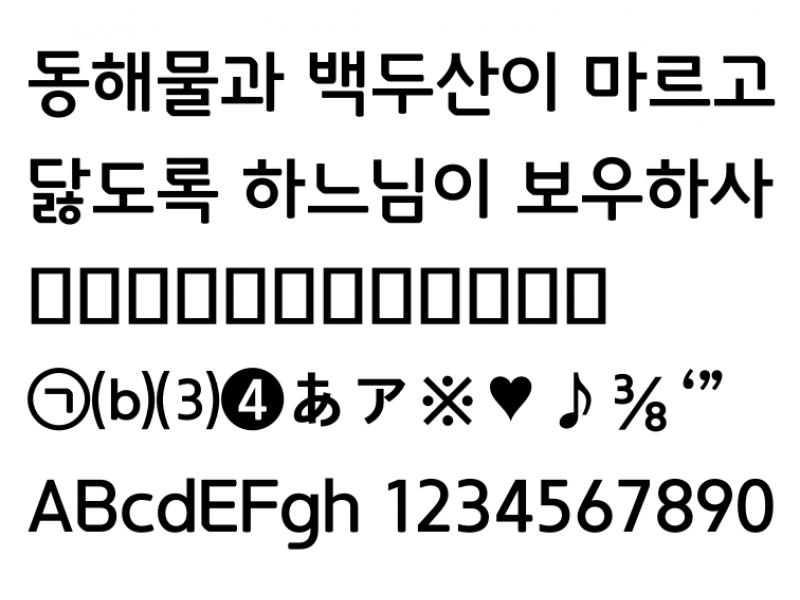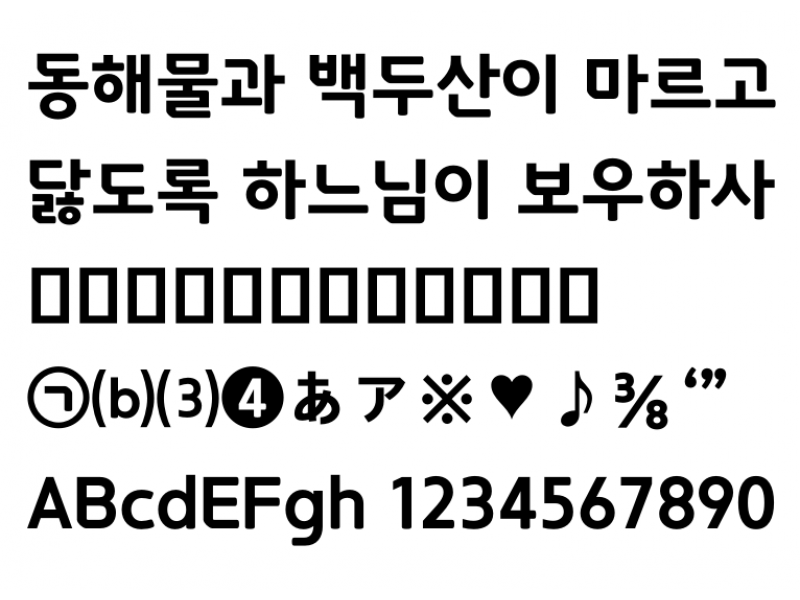
고도체는 엔에이치엔고도와 윤디자인연구소가 협력하여 만든 다이아몬드 형태의 심플하고 모던한 디자인의 많은 사랑을 받고 있는 글꼴이다.
고도체는 Medium, Bold 총 2종으로 구성되어 있다. 한글은 유니코드 기반의 2,350자를 지원하며 영문 95자, KS심볼 986자를 지원한다.